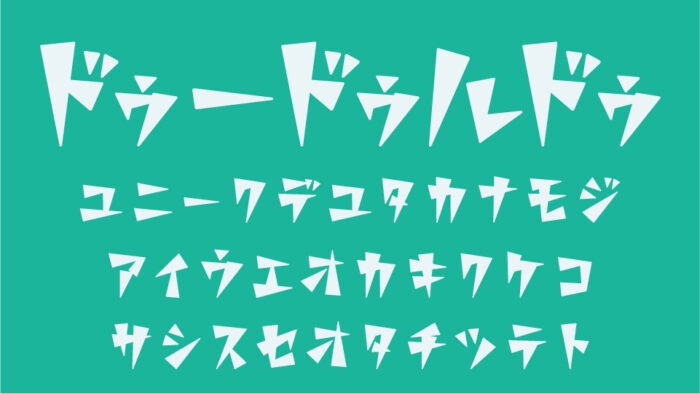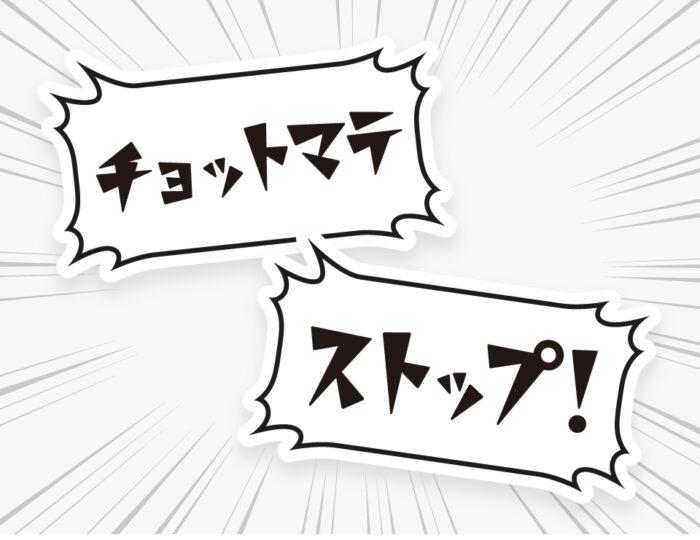
ドゥードゥルドゥ
ドゥードゥルドゥフォントは、ギザギザとした輪郭が特徴で、尖った形状とリズミカルなレイアウトがユニークなデザインフォントです。
ポップさの中に少しの毒っ気や反骨精神を感じさせるデザインで、ちょっと怒りな感情を感じさせてくれるフォントです。
トゲトゲで個性的ながらも楽しげでコミカルな空気があるので、漫画やテロップなどの吹き出しにもぴったりです。
収録文字は、カタカナ・アルファベット・数字・記号が収録されています。